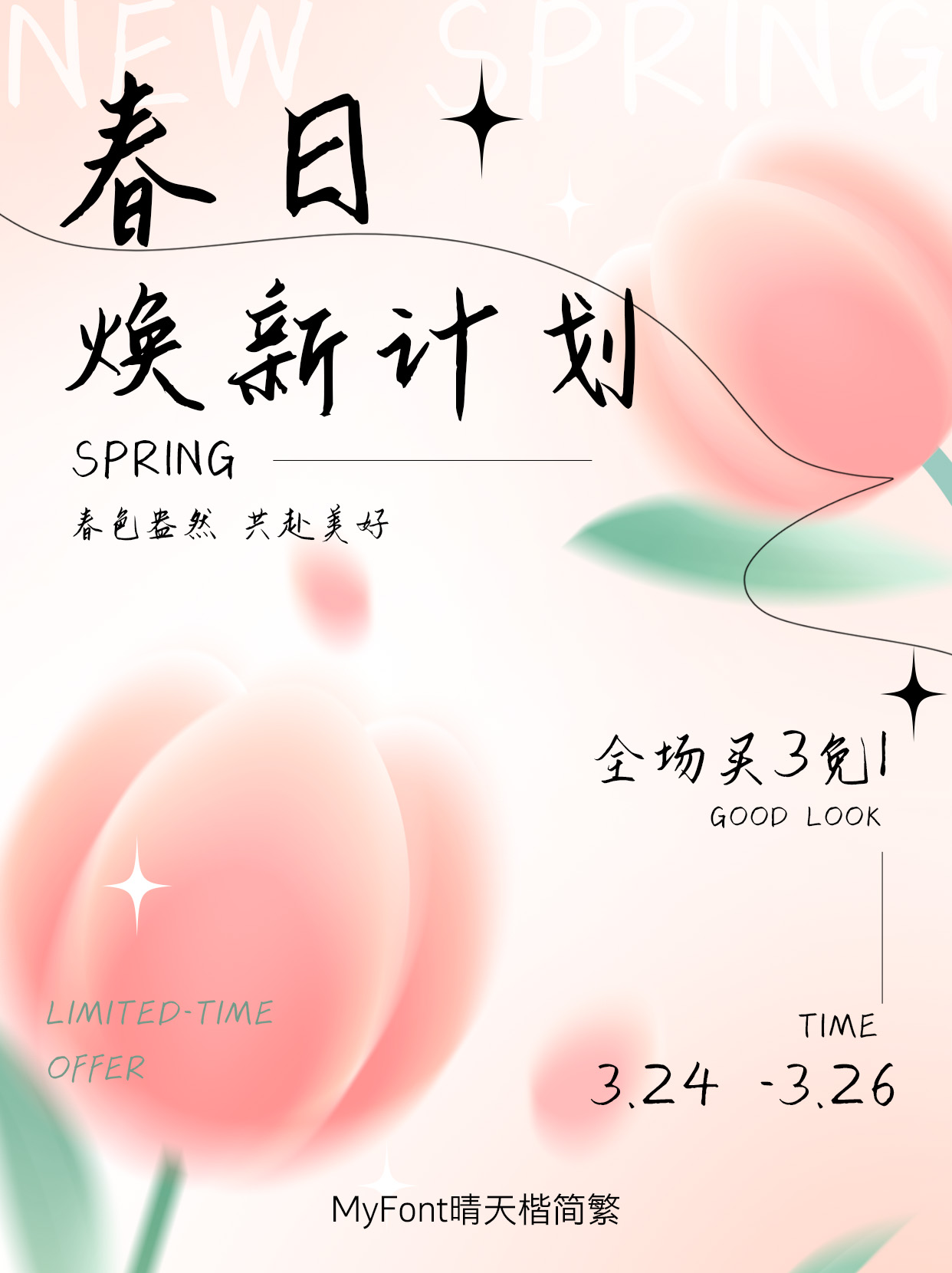
MyFont晴天楷简繁,
MyFont晴天楷简繁是一款灵动率意的手写字体。其运笔洒脱且富有力度,展现出硬笔书写的独特魅力。结体规整大方,主笔画肆意出锋,正如阳光正好,微风不燥的时刻,散发出独特光芒。此款字体不仅适用于书写正式文件、报告,还可用于书籍设计、品牌设计、包装、海报、广告等多种应用场景。
字圈也字圣诞快乐,
字圈也字圣诞快乐,以圣诞为准,加入圣诞元素,此款字体从字形结构来看,横斜竖直,左低右高,折笔处大为钝角,小为直角;棱角时而圆润,时而尖锐,从字体性格来看,笔画坚定,走向自信,不会在乎他人看法,遵从自我的内心。
字圈也字综艺弹幕体,
字圈也字综艺弹幕体,适用于综艺弹幕使用,此款字体从字形结构来看,横斜竖直,左低右高,折笔处大为钝角,小为直角;棱角时而圆润,时而尖锐,从字体性格来看,笔画坚定,走向自信,不会在乎他人看法,遵从自我的内心。